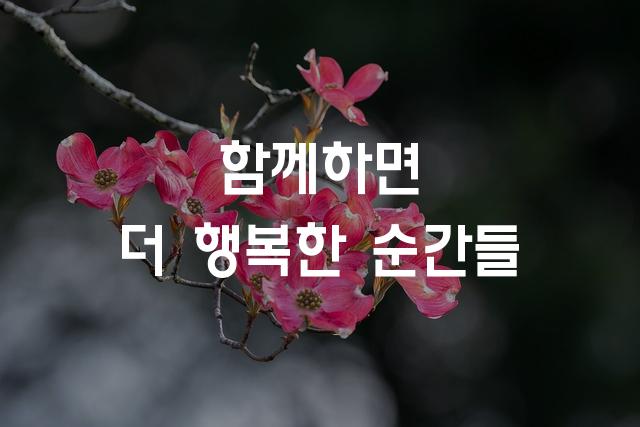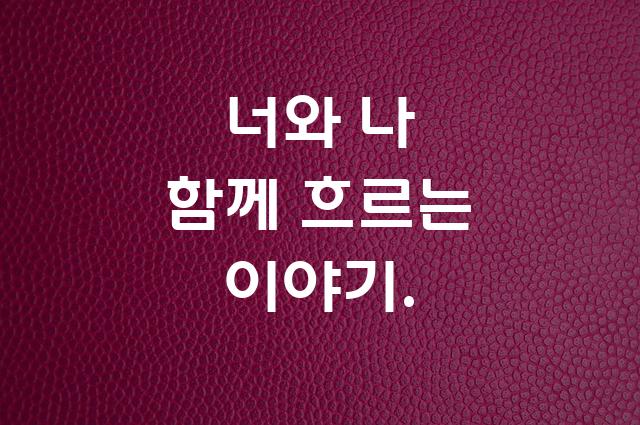
코레일 장체는 깔끔하고 현대적인 기본 고딕체로, 키가 큰 글자 디자인이 특징입니다. 넓은 활용도와 뛰어난 가독성을 제공하는 폰트입니다.
코레일 장체은(는)
기본 고딕, 두꺼운 스타일, 감성적인, 부드러움, 길고/크고 계열의 생김새를 가지고 있으며
웹/앱 디자인, 프레젠테이션, 보고서/문서 등에서 자주 활용되며, 효과적인 메시지 전달에 적합합니다.
이 폰트는 기술/IT, 공공/정부, 관광/여행 분야에 잘 어울리며,
신뢰감, 명확한, 전문적인 느낌을 담고 있는 것이 특징입니다.